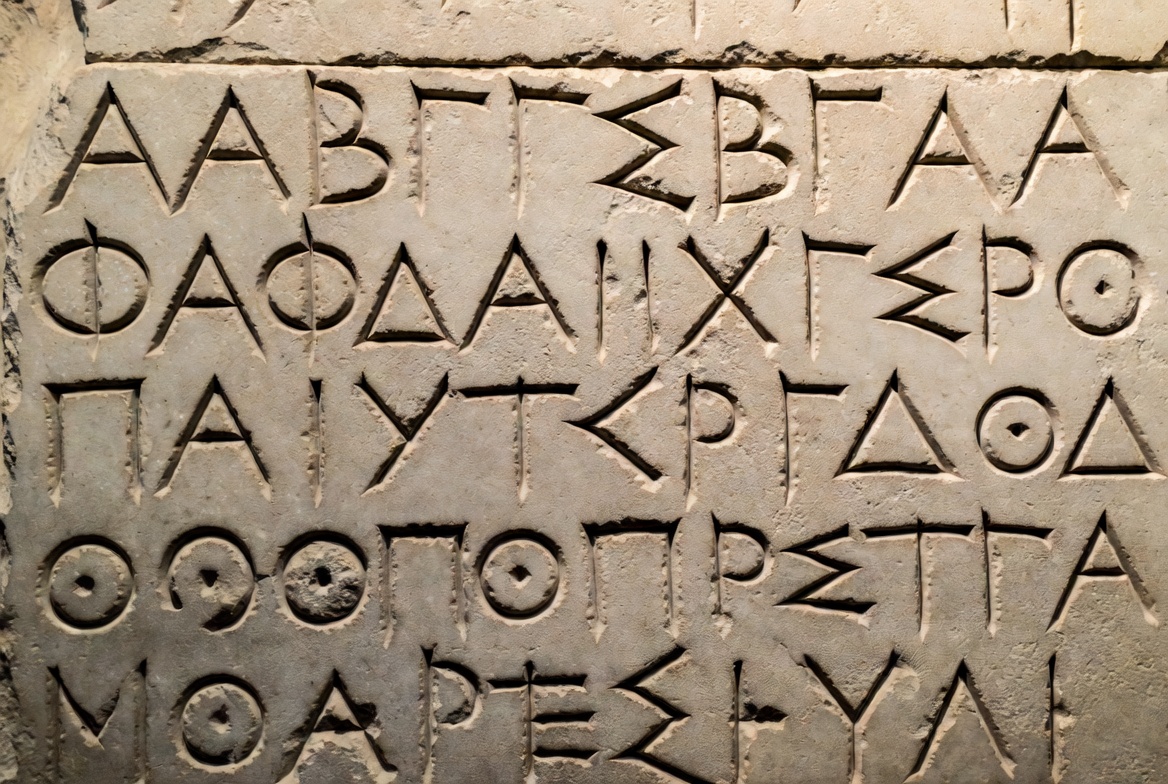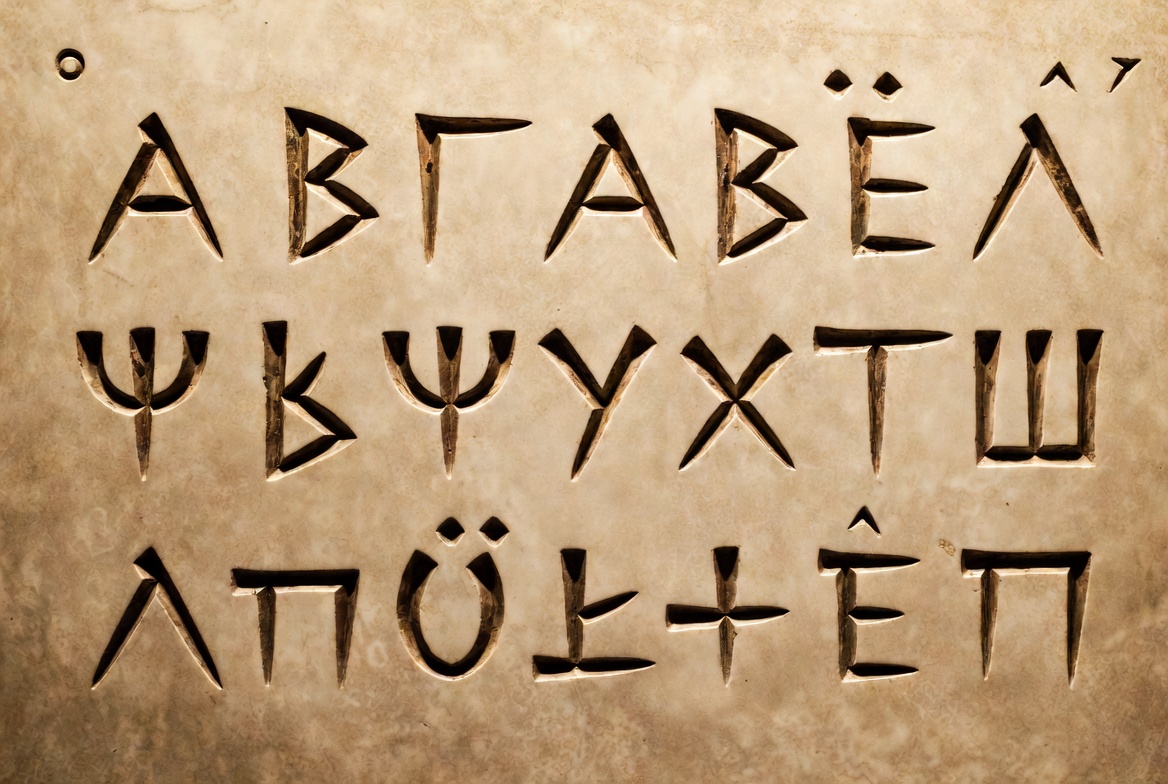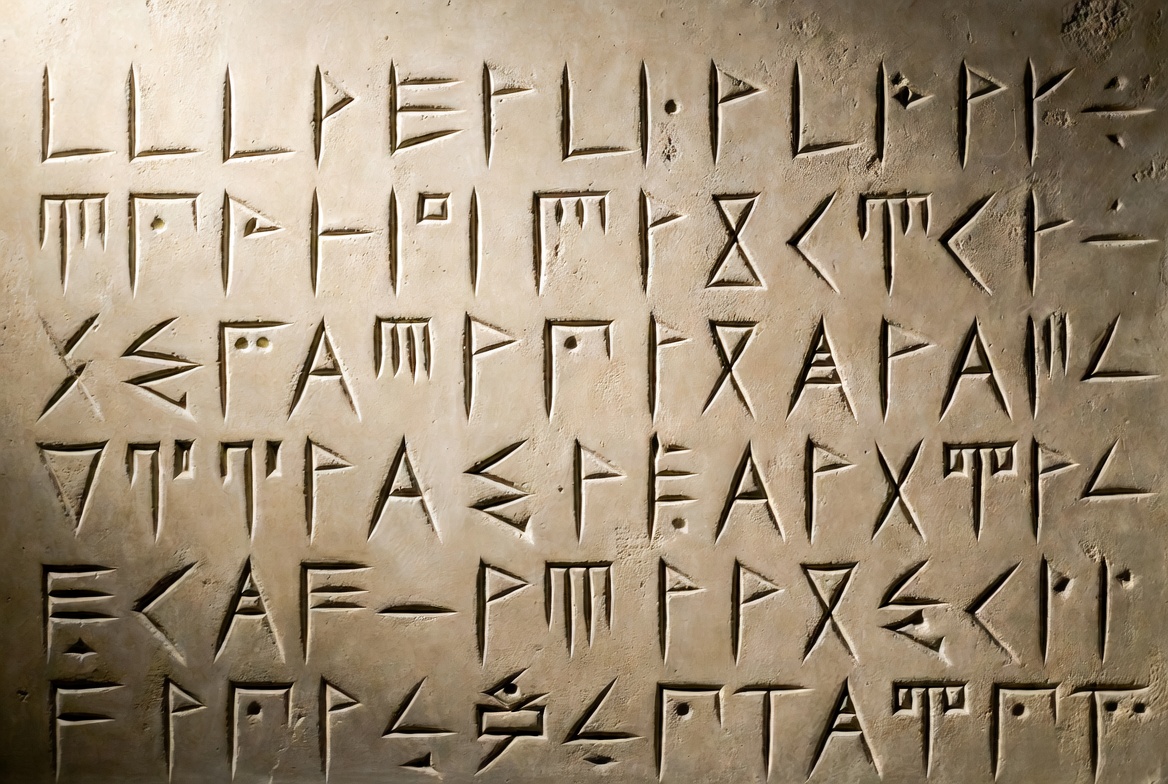
Geschichte der Schrift – Teil 2: Vom Bildzeichen zum Alphabet
Wie aus Bildzeichen und Silbenschriften das Alphabet entstand – und warum es die Schriftgeschichte grundlegend veränderte.
Im ersten Teil dieser Serie haben wir gesehen, dass die frühesten echten Schriften in Mesopotamien und Ägypten entstanden. Diese Systeme waren leistungsfähig, aber auch kompliziert: Wer schreiben und lesen wollte, musste Hunderte oder sogar Tausende von Zeichen beherrschen.
Der nächste große Schritt in der Geschichte der Schrift war die Entwicklung eines deutlich einfacheren Systems – des Alphabets.
Von Bildzeichen zu Silben und Lauten
Die frühen Schriften funktionierten vor allem nach dem Prinzip der Bild- und Ideogramme: Ein Zeichen stand für einen Gegenstand, einen Begriff oder eine Silbe. Mit der Zeit wurden die Zeichen abstrakter und abstrakter, und es entstanden gemischte Systeme, die sowohl Wort- als auch Lautwerte darstellen konnten.
Ein entscheidender Fortschritt war die Idee, nicht mehr ganze Wörter oder Silben, sondern möglichst kleine Lauteinheiten festzuhalten. Diese Entwicklung führte zu den ersten alphabetischen Schriften.
Die Proto-Sinaitische Schrift
Als älteste bekannte alphabetische Schrift gilt die sogenannte Proto-Sinaitische (auch Proto-Kanaanäische) Schrift. Sie entstand vermutlich im 2. Jahrtausend v. Chr. (ca. 1800–1500 v. Chr.) auf dem Sinai und in der Levante.
Illustration der Proto-Sinaitischen Schrift
Interessant ist, dass sie stark von den ägyptischen Hieroglyphen beeinflusst wurde. Semitisch sprechende Arbeiter und Händler übernahmen einzelne Hieroglyphenzeichen, gaben ihnen aber neue Lautwerte nach dem Prinzip der Akrophonie: Das Zeichen stellte den Anfangslaut des betreffenden Wortes dar.
Damit war der Grundstein für ein Konsonantenalphabet (Abjad) gelegt – ein System mit deutlich weniger Zeichen als die älteren Schriften.
Das Phönizische Alphabet
Aus der Proto-Sinaitischen Schrift entwickelte sich das Phönizische Alphabet. Es war um 1050 v. Chr. bereits voll ausgeprägt und bestand aus etwa 22 Zeichen, die ausschließlich Konsonanten darstellten.
Illustration des Phönizischen Alphabets
Die Phönizier waren seefahrende Händler. Durch ihre Handelskontakte verbreitete sich ihr Alphabet im gesamten Mittelmeerraum. Gerade diese Verbreitung machte das System so einflussreich.
Die griechische Innovation: Vokale
Den entscheidenden Schritt zur modernen alphabetischen Schrift vollzogen die Griechen. Sie übernahmen das phönizische Konsonantenalphabet und passten es an ihre Sprache an.
Illustration eines frühen griechischen Alphabets
Dabei nutzten sie einige Zeichen, die im Griechischen nicht benötigte Konsonanten darstellten, für Vokale. Damit entstand zum ersten Mal ein vollständiges Alphabet, das sowohl Konsonanten als auch Vokale systematisch abbildete.
Diese Innovation machte das Lesen und Schreiben deutlich einfacher und präziser. Das griechische Alphabet wurde zur Grundlage vieler späterer Schriften – darunter auch das lateinische Alphabet, das wir heute verwenden.
Warum das Alphabet so erfolgreich war
Der große Vorteil des Alphabets liegt in seiner Einfachheit:
- Statt Hunderter oder Tausender Zeichen genügen wenige Dutzend.
- Das System ist leichter zu erlernen.
- Es lässt sich flexibel an verschiedene Sprachen anpassen.
Genau diese Eigenschaften haben dazu beigetragen, dass alphabetische Schriften sich langfristig gegenüber den älteren, komplexeren Systemen durchsetzen konnten.
Ausblick
Mit dem Alphabet war ein grundlegend neues Prinzip der Schrift gefunden. Im nächsten Teil dieser Serie beschäftigen wir uns damit, wie sich die Schrift im Mittelalter weiterentwickelte und wie die Erfindung des Buchdrucks die Verbreitung von Schriften und Texten revolutionierte.